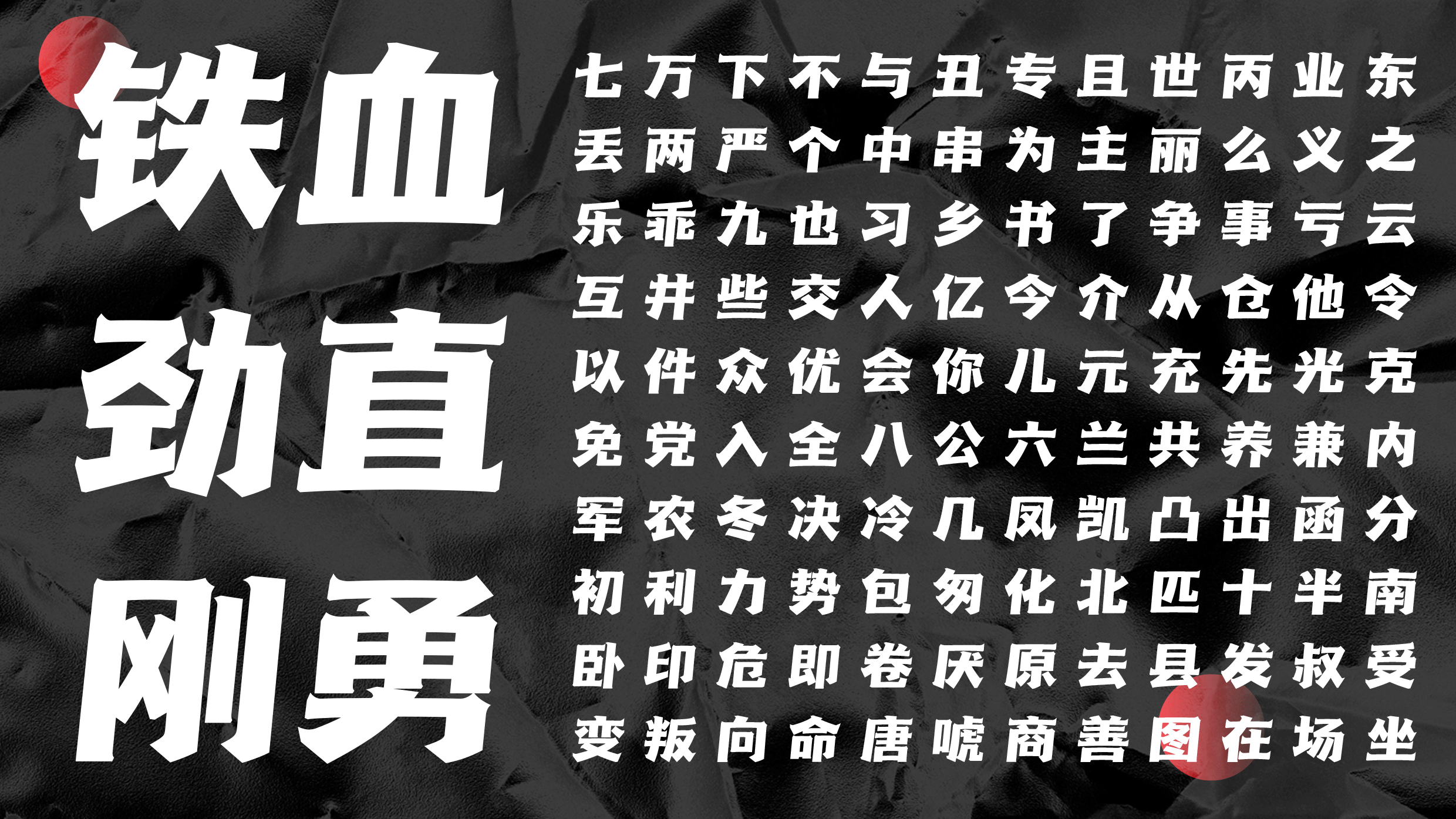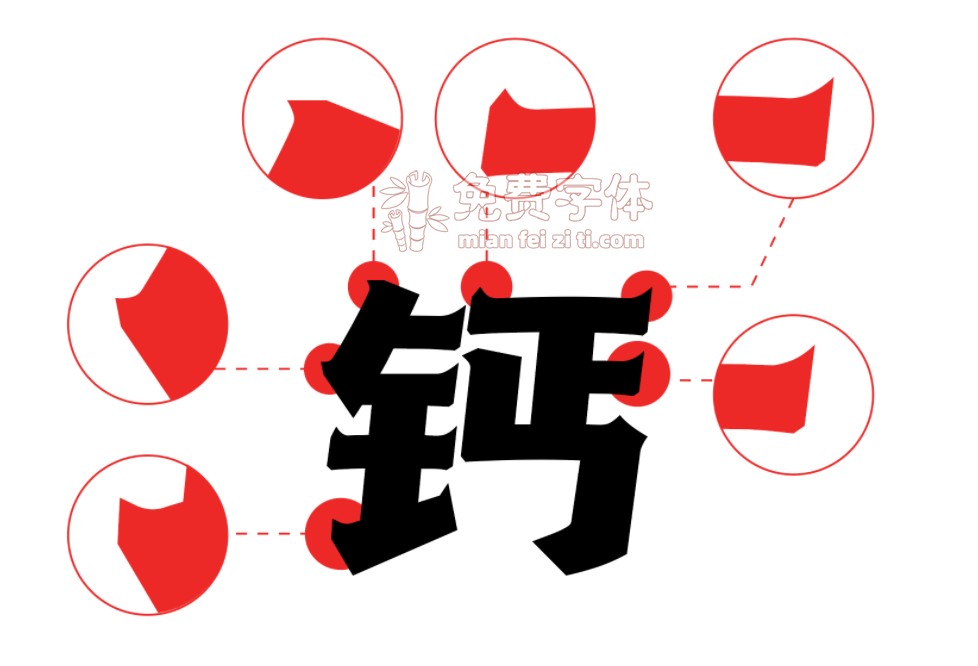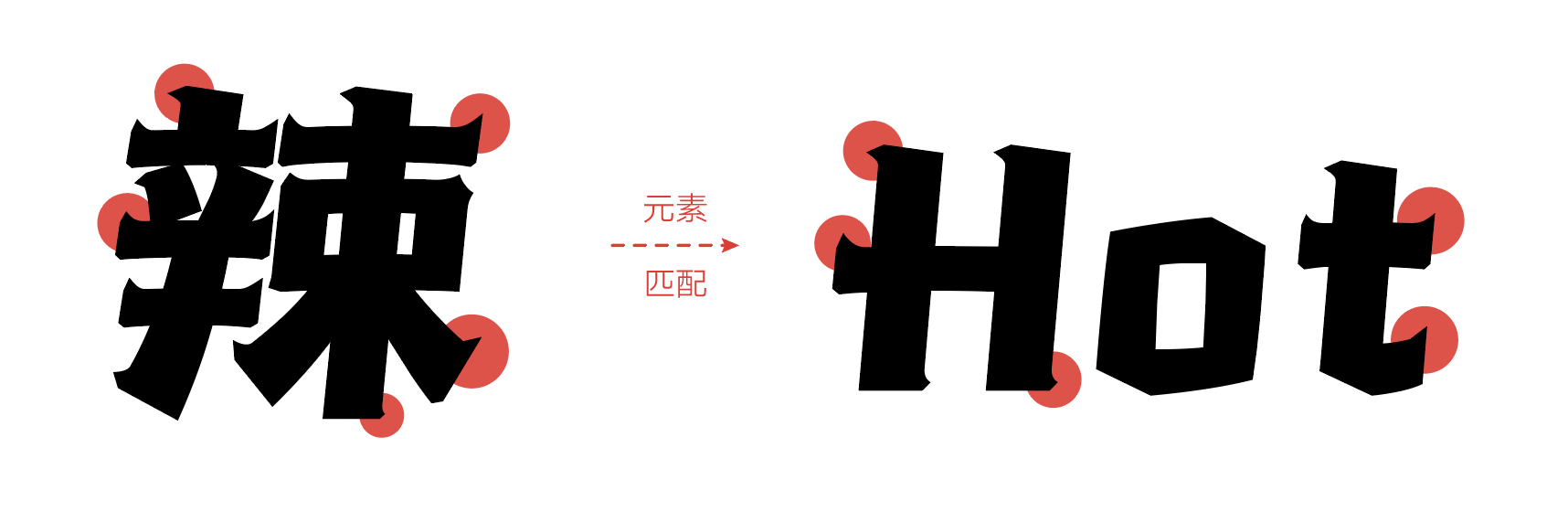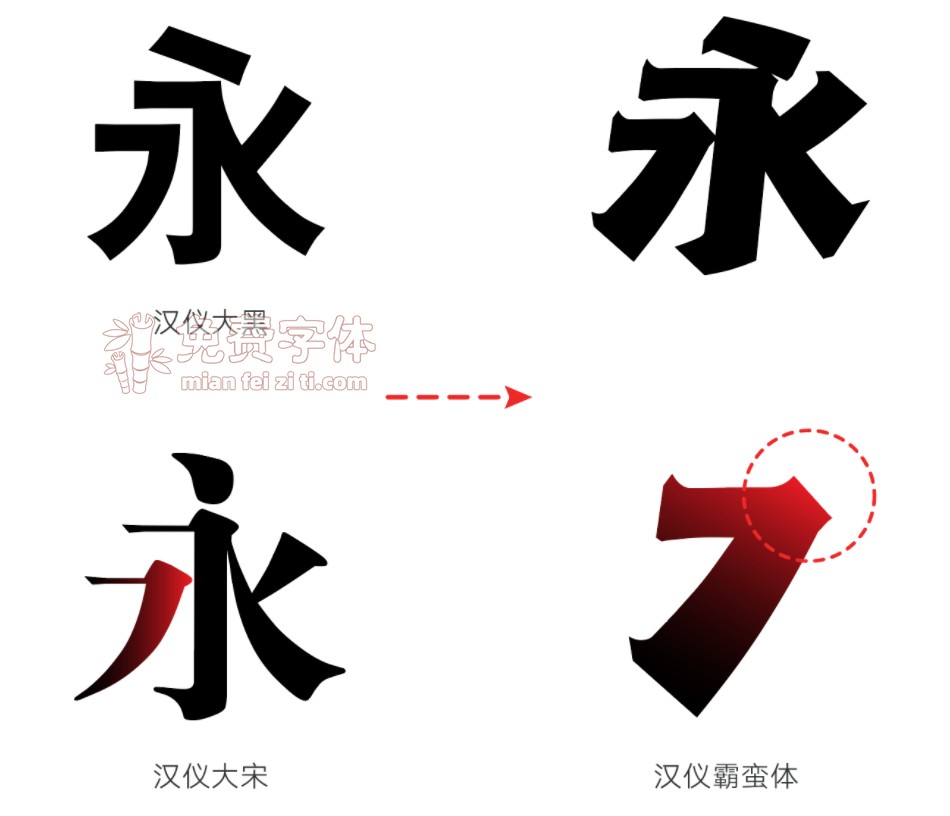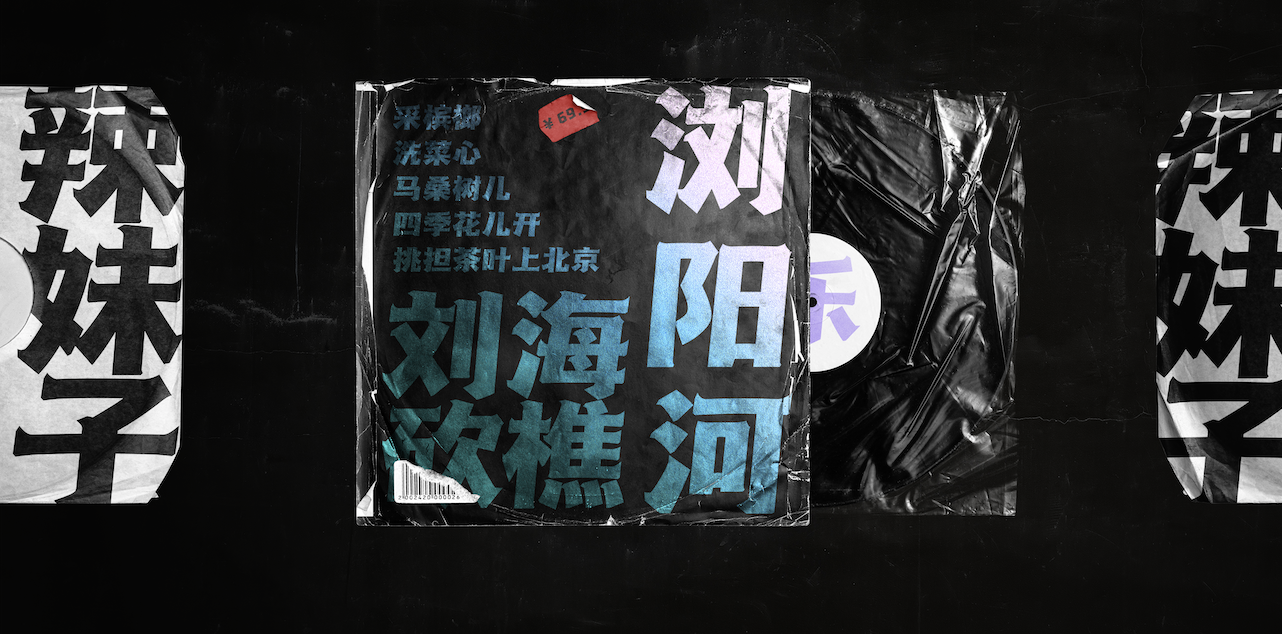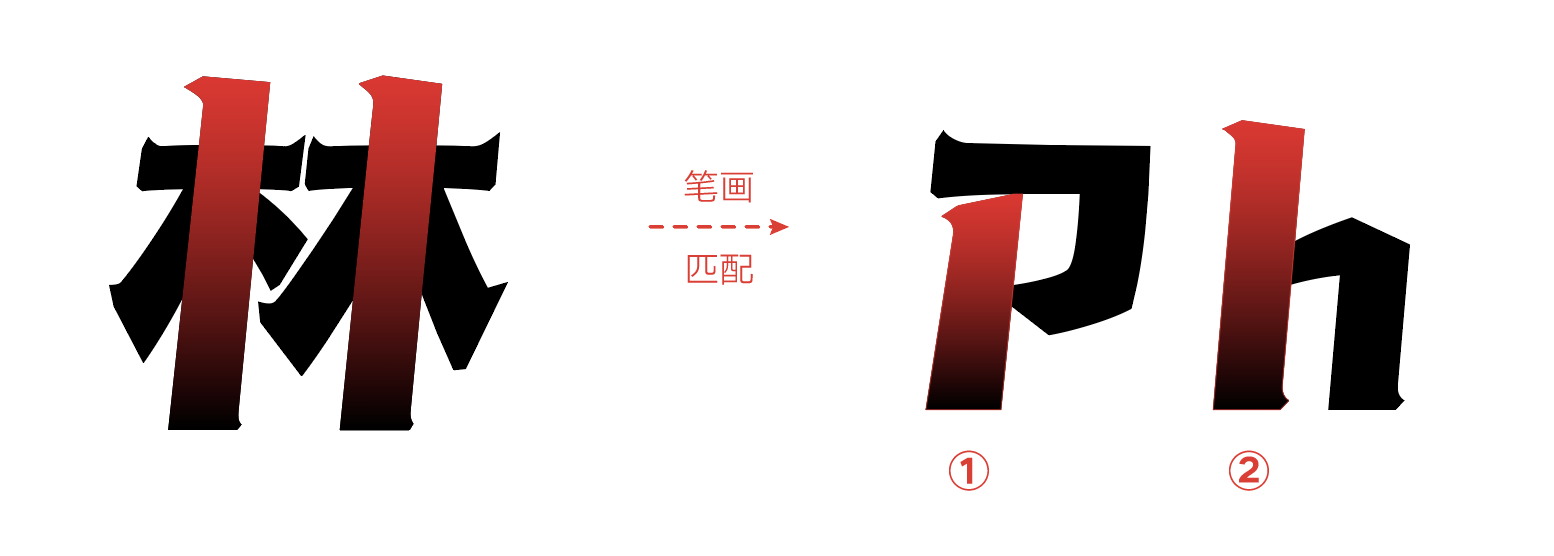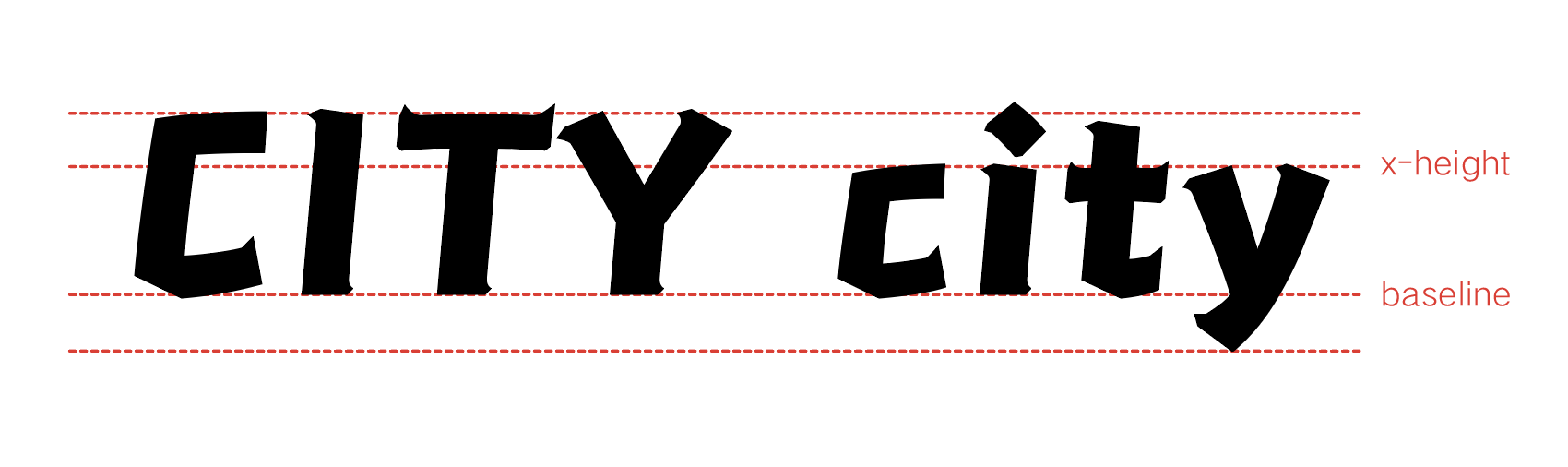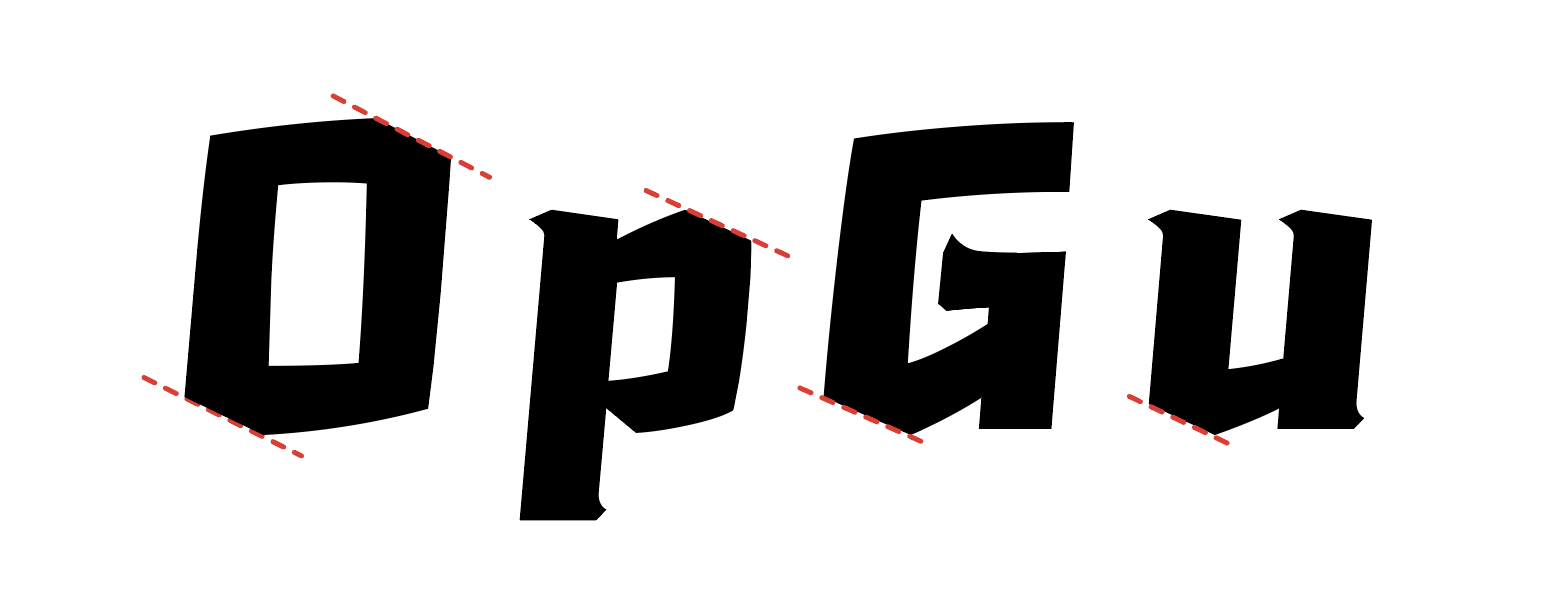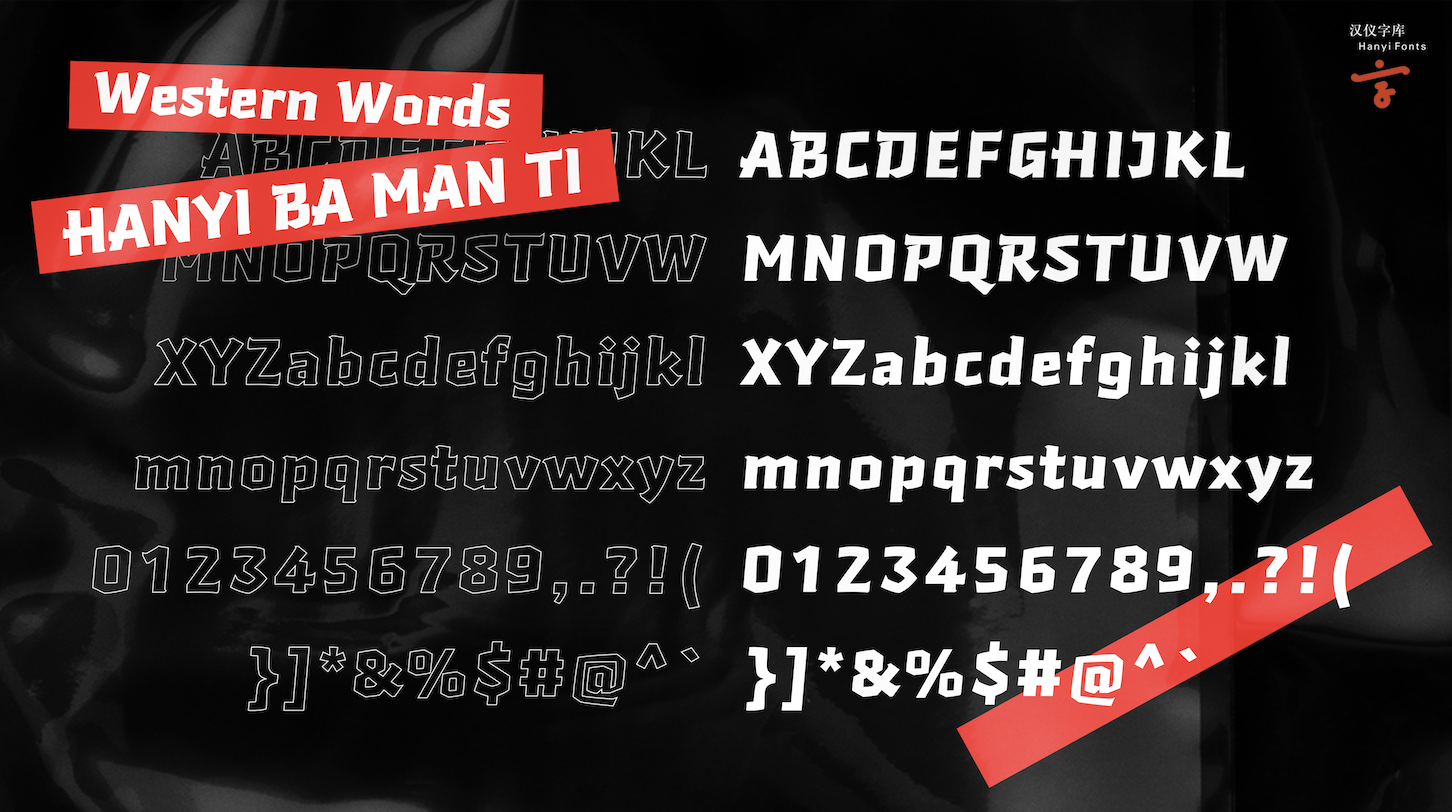
汉仪霸蛮体 | 具有地域特色的中文字体字体资讯
地域特色字体
汉仪霸蛮体是中国首款表达地域文化精神的IP字体。
汉仪霸蛮体将湖南精神进行了高度抽象化。湖南省位于长江中游,省境绝大部分在洞庭湖以南,故称湖南;湘江贯穿省境南北,故简称湘。一方水土养一方人,湖南独特的地理环境造就了独特的群体个性,并培育造就出湖湘人民忠诚、担当、求是、图强、胸怀天下、务实、创新、霸蛮的精神特点。
字体名称中“霸蛮”是湖南方言。意思是执着,在困难中吃得苦,有干劲。“霸”是指霸气,但不霸道;“蛮”是指有蛮劲,霸得蛮,耐得烦。 “霸蛮”是湖湘文化中重要的精神元素,它涵盖了湖南人敢为人先、沉着坚毅、勇于担当的铁血精神。
设计理念
再大再抽象的文化与事物,如果要用字体设计去表述,还是要拆解成细节, 如一撇一捺,再将想要表达的思想融入字体的横竖笔画中,以字发声。汉字虽小,但依然能够承担大气势,正所谓, 小文字,大气象。设计师以“霸蛮”为字体设计的基调,将湖湘人民坚韧直爽的性格特征、刚劲务实百折不挠的精神文化内涵以及湖南名人的书法特点融入在字体中,最终设计出“汉仪霸蛮体”。
刚劲有力
汉仪霸蛮体的重心偏高,中宫放松,笔画粗壮、锋利、干脆,横轻竖重,起笔收尾呈三角状,刚劲有力,兼具古朴与现代感。
结构动感
汉仪霸蛮体的字型扁宽呈斜势,呈现出平行四边形的外轮廓,斜线相对于直线更有一种激进向前的运动效果,这与湖湘精神中的敢为人先不谋而合。
融古于今
汉仪霸蛮体将宋体字的笔画、黑体字的结构和书法的特点相结合,降低了宋体字收笔笔势的识别度,兼具印刷字体和书写字体的美感。
参照毛泽东的书法,在捺画的收笔处上提形成一个勾画,使字体更加有力度,凸显 “霸蛮”气质。
横画参借用了欧阳询《房彦谦碑》中横画的特点,行笔中段微向上提笔,将横画做出弧度。直线略微向上弯曲,像扁担状,表达湖南人骨子里透漏出的力量感和担当精神。
在双点划的设计上,参考了曾国藩的书法字体。表现湖南人不守常规,敢为人先的精神特点。
线条简洁
湖南人性格中另一大特点就是直爽不做作,直线的处理更能突显出力量感,所以在撇和捺画的设计中减少了弧线的运用,抹去多余的细节,避免过度的曲线给字体带来妖娆感。
笔画减少弧度的出现,将曲线部分减弱,并且加入“尖角”的装饰元素。首先是为了体现极简的设计风格,再者将收笔处锐化旨在体现湖南人刀刚火辣的性格和无辣不欢的饮食特征。
中西文匹配
汉仪霸蛮体西文的设计来源于对中文的充分解读,从中文设计中提取了可借鉴的字形、笔画和装饰元素。
1、汉仪霸蛮体的西文与中文相同,都是向右倾斜。
2、汉仪霸蛮体的西文造型与中文字体笔画的“尖角”元素相呼应,使得中西文搭配使用十分和谐。
3、汉仪霸蛮体西文字母的细节处理别出心裁,它有两种形态的竖画,给字体增添出一些趣味
4、汉仪霸蛮体的西文在大小写曲线字母的处理上采用了折笔直线,笔画外折内方,与中文相呼应,弱化弧线,让字形更加直爽刚强。
5、汉仪霸蛮体的西文字母调整了结构比例,放大了x-height,实现了字体的性格特点。